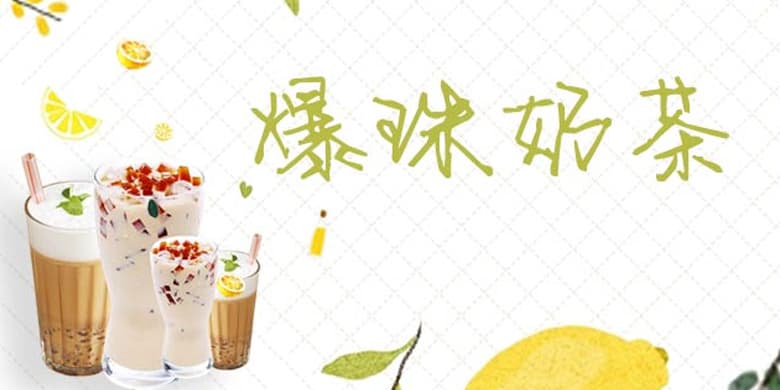
品牌:方正手迹设计师:瞿颖发行时间:2020字库编码:大陆简体(GB2312-80)分类:常规书写·硬笔字体属性:精品字
字体结构隽秀严谨,又不失潇洒灵动。用笔张弛有度、从容不迫,字体排列错落有致,深具书写之美感。即使连笔较多,也不影响良好的阅读体验。适用于文艺类的书刊、品牌广告和产品包装设计,以及社交网络的个性化用字。